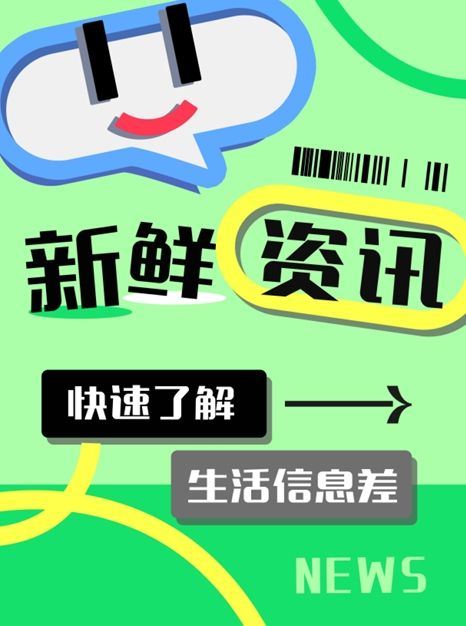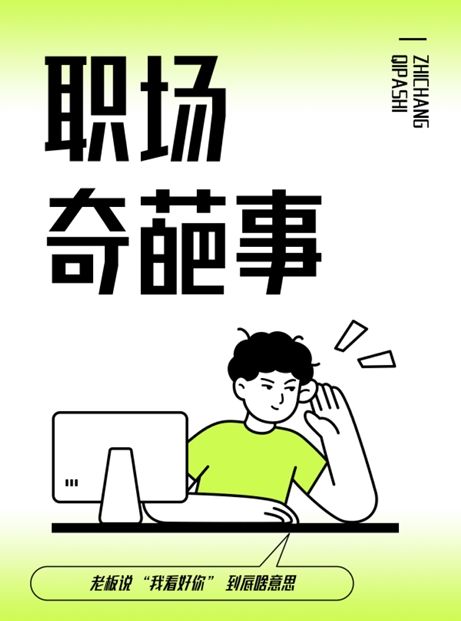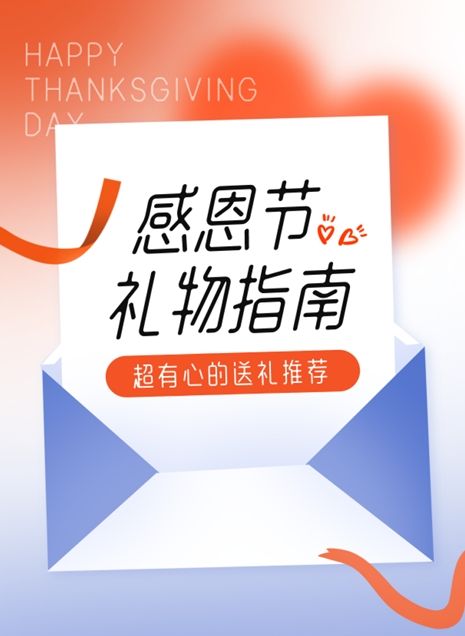
高手庆科字体合集:书写创意,共绘字体行业华章!
随着造字侠高手字造计划的盛大招募启幕,我们迎来了一个充满创意与激情的字体设计盛宴。在这个汇聚众多字体设计高手的平台上,庆科字体以其独特的风格和魅力,成为了众多设计师的心头好。今天,就让我们一起来欣赏并推荐这些令人瞩目的庆科字体吧!
庆科字体,以其独特的创意和精湛的设计技艺,成为了字体设计界的一股清流。这些字体不仅具有极高的艺术价值,更能够在实际应用中发挥出巨大的作用。无论是用于品牌标识、广告宣传还是包装设计,庆科字体都能以其独特的风格,为作品增添一份独特的魅力和个性。
在庆科字体的设计过程中,设计师们注重将传统与现代相结合,通过独特的线条和造型,展现出一种既有古典韵味又不失现代感的美学风格。这些字体既能够传递出传统文化的精髓,又能够符合现代审美的需求,让人们在欣赏的同时,也能感受到一种文化的传承与延续。
此外,庆科字体还注重实用性和可读性的平衡。设计师们在追求创意的同时,也充分考虑到了字体在实际应用中的效果。因此,这些字体不仅具有极高的艺术价值,更能够在实际应用中发挥出良好的作用,为作品增添一份独特的风格和个性。
造字侠高手字造计划的招募启幕,为字体设计界注入了新的活力和创意。而庆科字体的加入,更是为这个平台增添了一份独特的魅力和个性。我们相信,在众多字体设计高手的共同努力下,庆科字体将能够发挥出更大的潜力,为字体设计界带来更多的惊喜和创意。